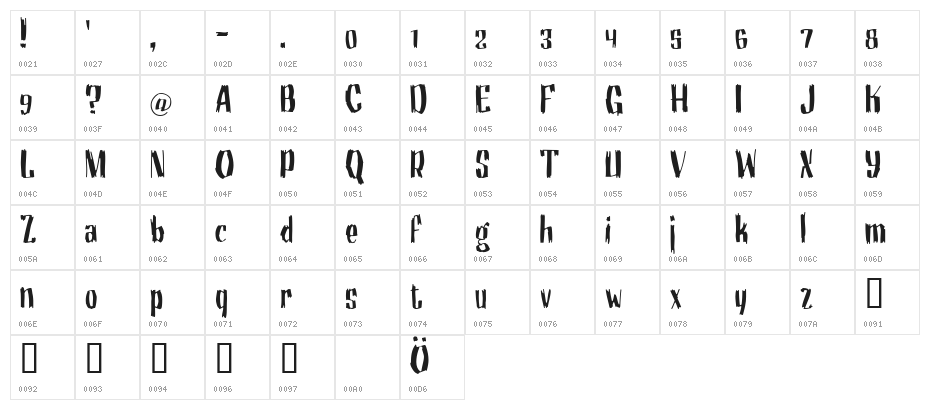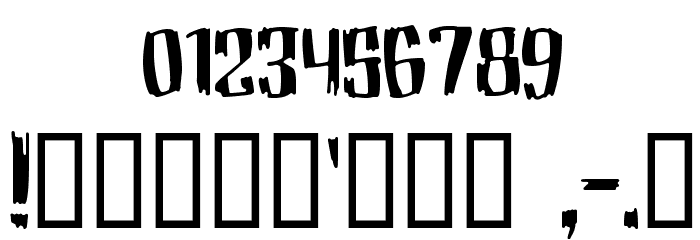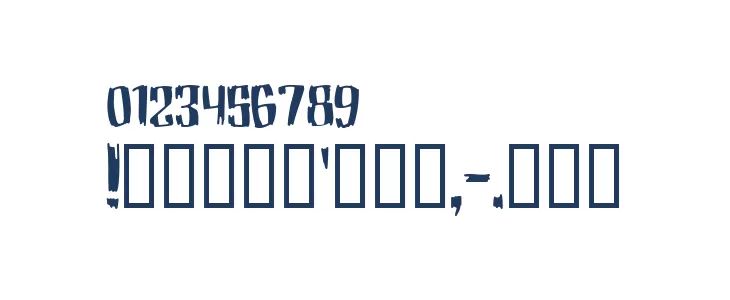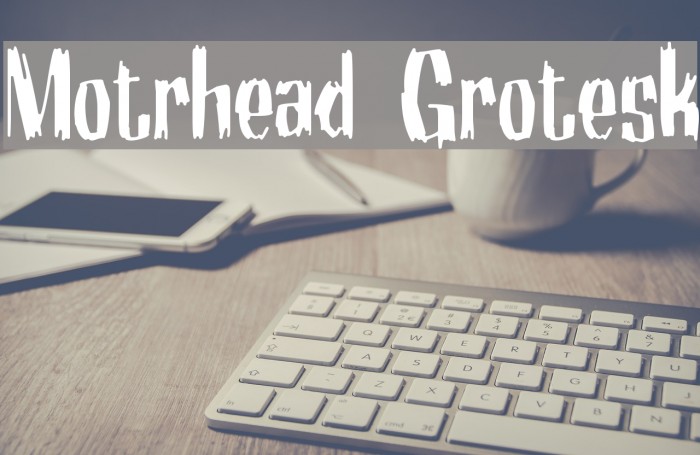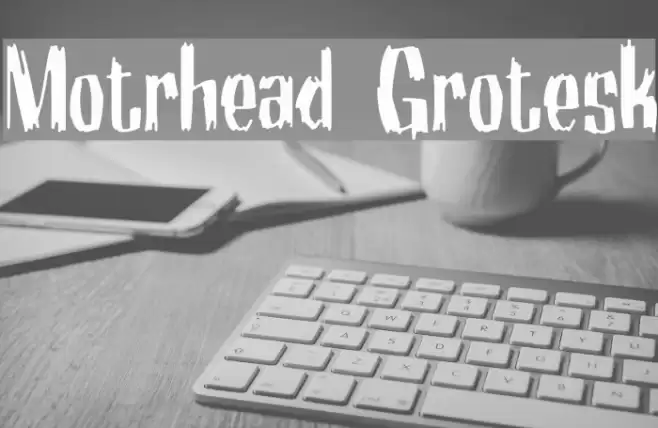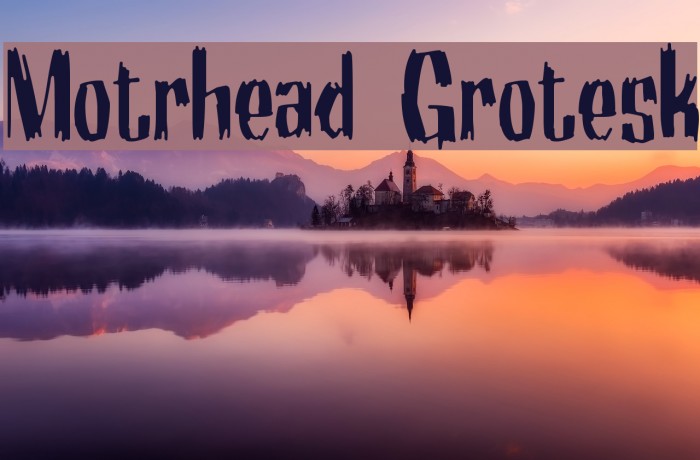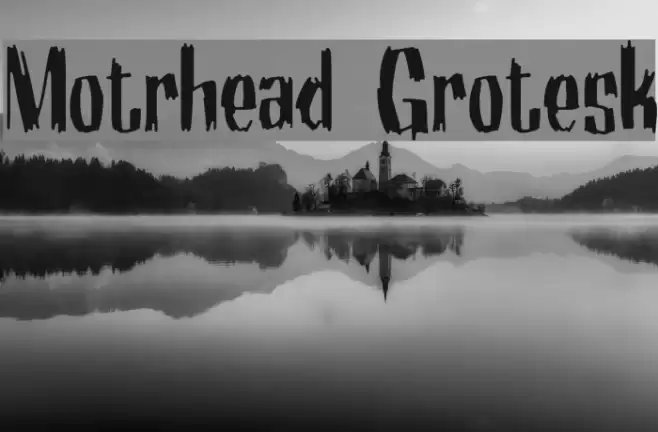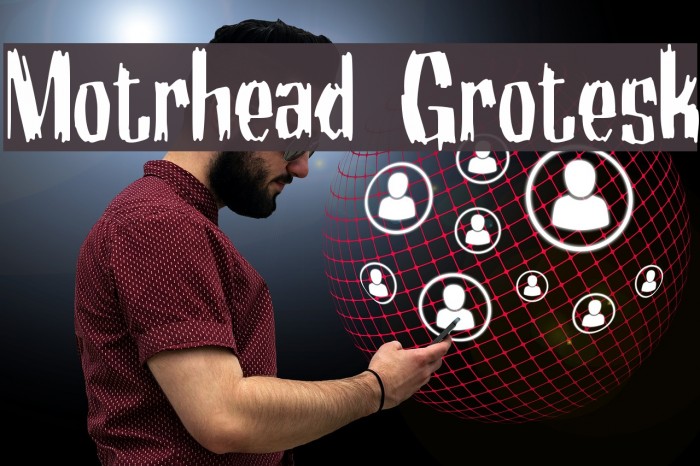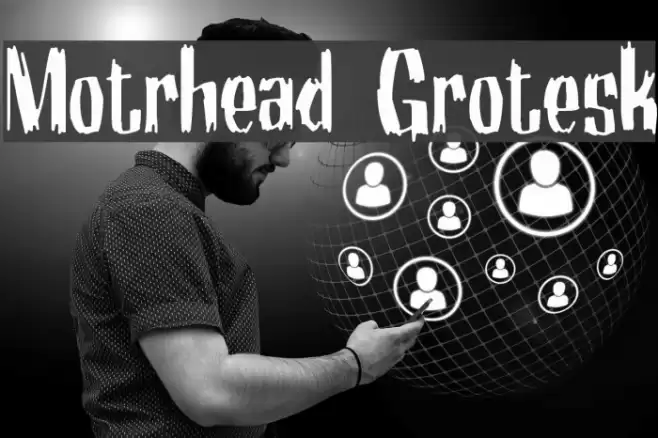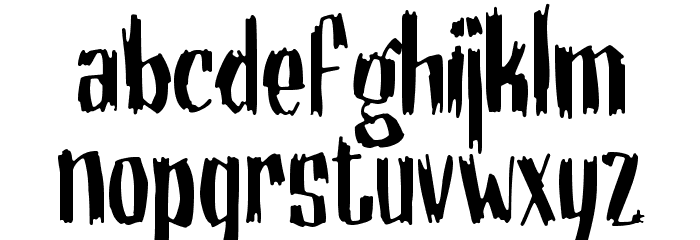
Motrhead Grotesk Font
Fonts by Patrick Broderick
| Область применения | Logos, Headlines, Posters |
| Рекомендуемые проекты | Ideal for music album covers, band logos, poster designs, and any project requiring a bold, edgy aesthetic. |